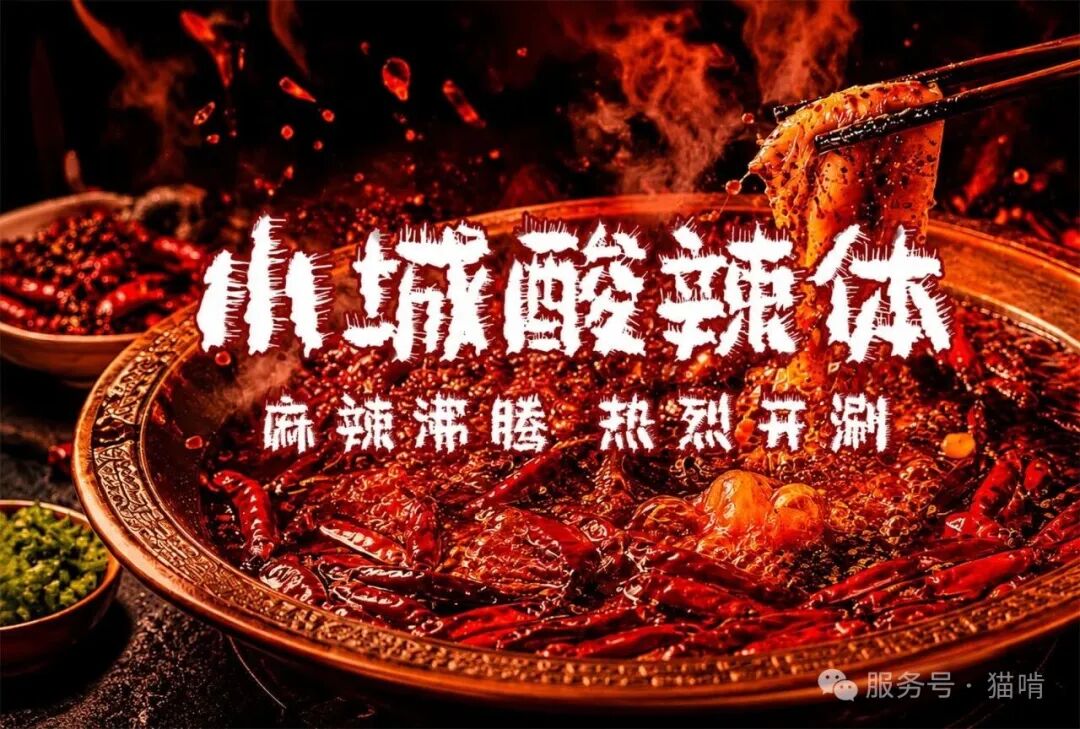
有的字体适合写下吃吃喝喝,有的适合收藏旧时光;有的属于森林、田野和远方,也有的像一轮早起的月亮。
当“小城”的生活气,遇见猫啃的正版字体集市
字体不只是信息的外衣,也能传递情绪、塑造氛围。小城字库的作品,从生活、情绪和想象中寻找灵感:既有轻松有趣的表达,也有安静细腻的叙事;既能接住人间烟火,也能写下森林、星愿和远方。
这次上线的26款字体,名字有趣,风格也各不相同。下面,我们分成四组,一款一款认识它们。
人间烟火,快乐有字可写
从吃喝日常到轻松玩梗,这一组字体自带亲和力和快乐感,适合餐饮、零食、亲子、社交媒体与节日促销。
01|小城吃吃喝喝体:把烟火气写得轻松又可爱
笔画自然松弛,字形带着手写的亲近感,放进餐饮画面里尤其有生活气。适合奶茶、甜品、探店、美食笔记、菜单标题和轻松促销。
02|小城哈哈体:像云朵一样轻快的治愈手写
字体轮廓柔软,书写节奏活泼,既能表达开心,也不会显得吵闹。适合治愈系海报、亲子内容、生活方式配图和年轻品牌的社交文案。
03|小城笑嘻嘻体:把快乐直接写在画面中央
粗细变化鲜明,字面醒目,带有直率又讨喜的手写感。适合节日活动、零食包装、短视频封面、直播标题和需要快速传递快乐情绪的设计。
04|小城囧哈哈体:像彩笔涂鸦一样天真有趣
字形不拘一格,带有儿童画般的自由和幽默感,配合插画会更显活泼。适合亲子活动、校园主题、儿童读物、手账、表情内容和趣味海报。
05|小城酸汤体:浓郁、热腾腾,一眼就有食欲
笔画厚重,边缘带有强烈的手作质感,大字使用时冲击力很足。适合酸汤、火锅、烧烤、夜市、餐饮招牌和高能促销标题。
06|小城酸辣体:麻辣沸腾,标题也要够带劲
字体走势舒展,笔触有速度感和辣劲,能够迅速把热烈氛围推到画面前景。适合川湘餐饮、辣味零食、夜宵活动、餐饮开业和短视频美食封面。
07|小城童真体:简单线条里,保留一颗童心
笔画清爽,字形带着稚拙而友好的手写感,画面容易显得轻松、明亮。适合儿童教育、亲子活动、玩具文具、成长记录和校园主题。
08|小城魔法体:森林深处,文字开始施展想象
略带粗粝感的笔触让字体显得神秘、奇幻,又保留了手写温度。适合奇幻故事、游戏活动、露营森林、万圣节和儿童冒险主题。
写给生活,也写给自己
这一组更擅长传递情绪:有安静、有希望,也有旧时光和月色,适合文艺内容、品牌故事、摄影配字与情绪海报。
09|小城文艺体:把一句心事,写进夜色里
字形纤细舒展,书写节奏自然,适合在留白和摄影画面中安静出现。可用于诗句、音乐、影像、旅行手账、书籍封面和文艺品牌内容。
10|小城盼望体:柔软明亮,像好消息正在靠近
字面温和,笔画圆润,既有手写温度,也有清晰的标题识别度。适合治愈内容、节日祝福、女性向品牌、成长记录和温柔促销。
11|小城星愿体:用涂鸦和小心愿点亮日常
带有马克笔和随手画的轻松感,字形活泼、记忆点鲜明。适合手账、文创、生日祝福、校园活动、年轻社交内容和可爱包装。
12|小城随缘体:松弛一点,也是一种生活态度
笔势自然流动,既有书写感,也带着一点随性和旷达。适合露营、旅行、生活方式、茶酒文化、户外活动和情绪短句。
13|小城孤独体:安静、克制,为画面留下一点余韵
字形修长,笔触有明显的个人书写气息,适合与留白、街景和人物背影搭配。可用于电影感海报、散文诗句、独立音乐、摄影作品和情绪叙事。
14|小城故事体:每一笔,都像在翻开一段往事
字体有较强的手作和叙事气质,放大后质感鲜明,适合承担故事标题。可用于纪录片、书影音、城市记忆、人物专访、展览和复古主题。
15|小城旧时光体:清清淡淡,写下值得回望的日子
字形修长清秀,带有轻微的复古感和手账气息。适合怀旧摄影、青春纪念、旅行明信片、节气海报、散文和品牌故事。
16|小城梦想体:圆润可爱,为愿望加一点勇气
字形松软活泼,线条像随手写下的愿望清单,亲切而不失个性。适合成长、毕业、招新、手账、文创和年轻化品牌传播。
17|早起的月亮:干净圆润,把月色写成温柔的光
线条简洁,字形圆润,现代感与梦幻感兼具,短标题尤其清晰。适合晚安内容、音乐歌单、治愈文案、儿童故事、节日祝福和星空主题。
去旅行,去自然里呼吸
海面、森林、田野与茶香,为字体带来更辽阔的呼吸感。适合文旅、户外、农产品、茶饮、民宿与自然生活方式品牌。
18|小城漂流记:顺着海风,找到自己的方向
字形轻盈舒展,笔势带有流动感,与海面、天空和大面积留白很合拍。适合旅行记录、海岛文旅、户外品牌、诗意摄影和自由主题。
19|小城遨游记:舒展有力,让出发更有气势
笔画开张,书写感鲜明,大字呈现时既洒脱又有速度。适合文旅主视觉、户外活动、城市宣传、航海主题和热血出发的内容。
20|小城森林体:质朴、有趣,像从草木间长出来
字体轮廓厚实,手作感突出,与植物、花朵和自然材质搭配很有亲和力。适合露营、环保、农产品、花店、自然教育和手工市集。